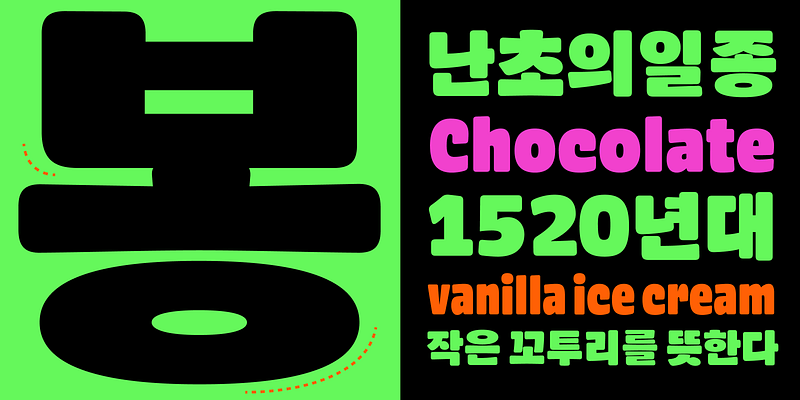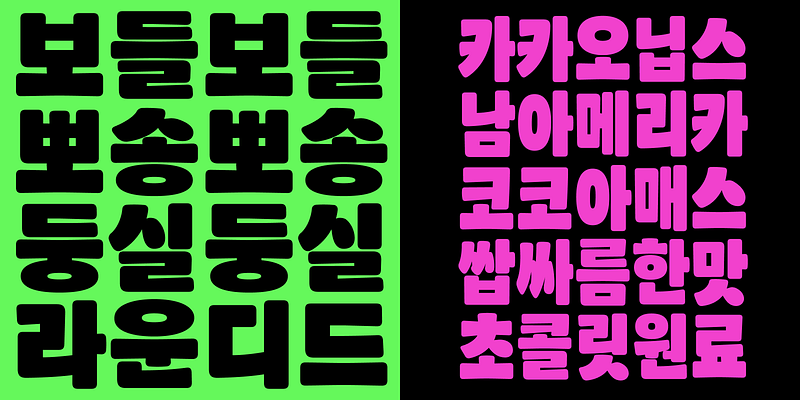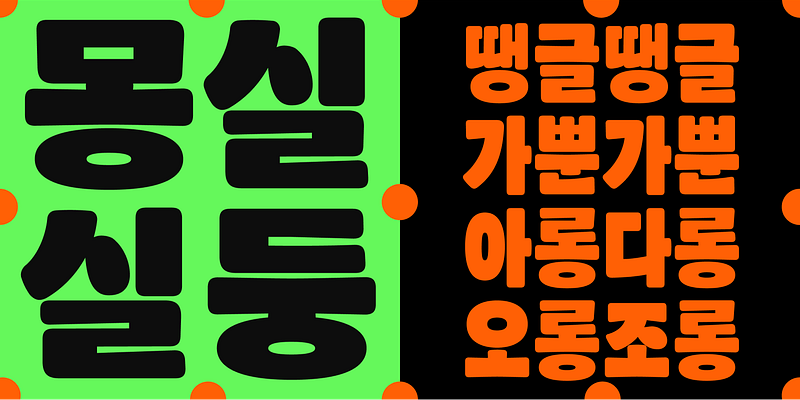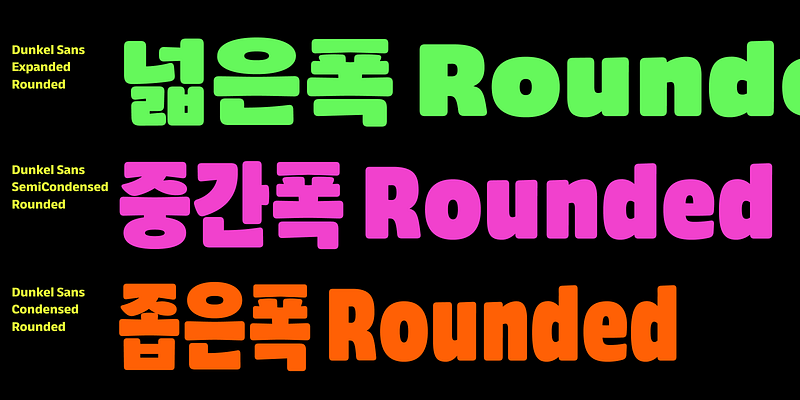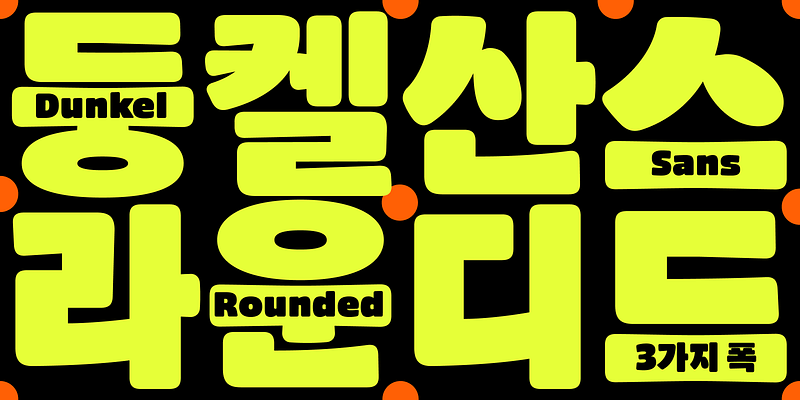
「Dongkelsans」の丸みを帯びたバージョンです。繊細でありながら独特のタッチのこのフォントは、ストロークの角を丸め、柔らかく親しみやすい雰囲気を感じさせます。
Minjoo Ham は、独立の書体デザイナーであり、Hypertype の 2 人の共同経営者の 1 人です。オランダ、ハーグの王立芸術アカデミーでタイプメディア修士課程を修了。学生時代はラテン文字とハングル文字のダブルスクリプトに精力的に取り組み、それ以来、マルチスクリプトフォントプロジェクト用のマルチスクリプトファミリーを開発し続けています。